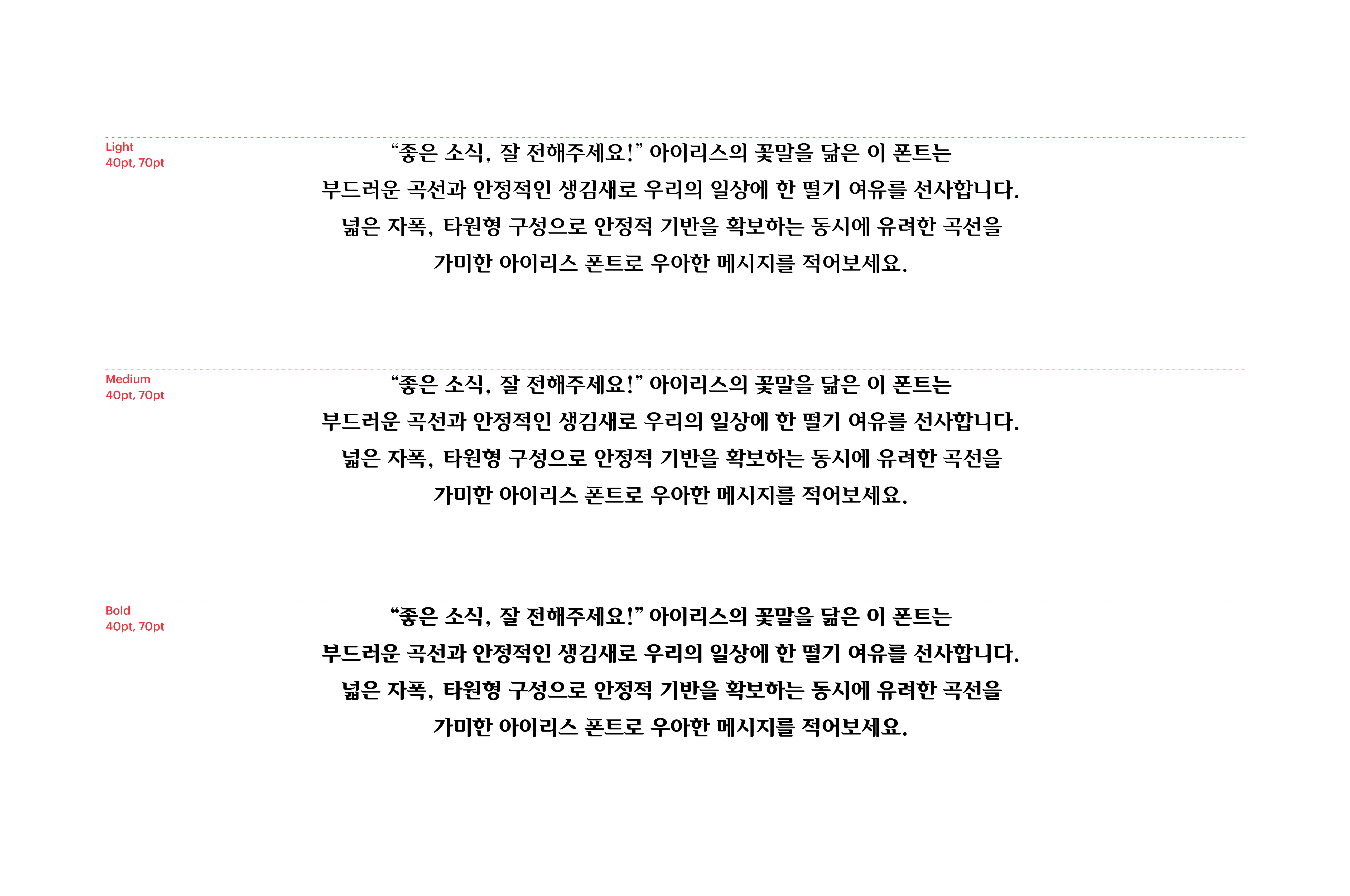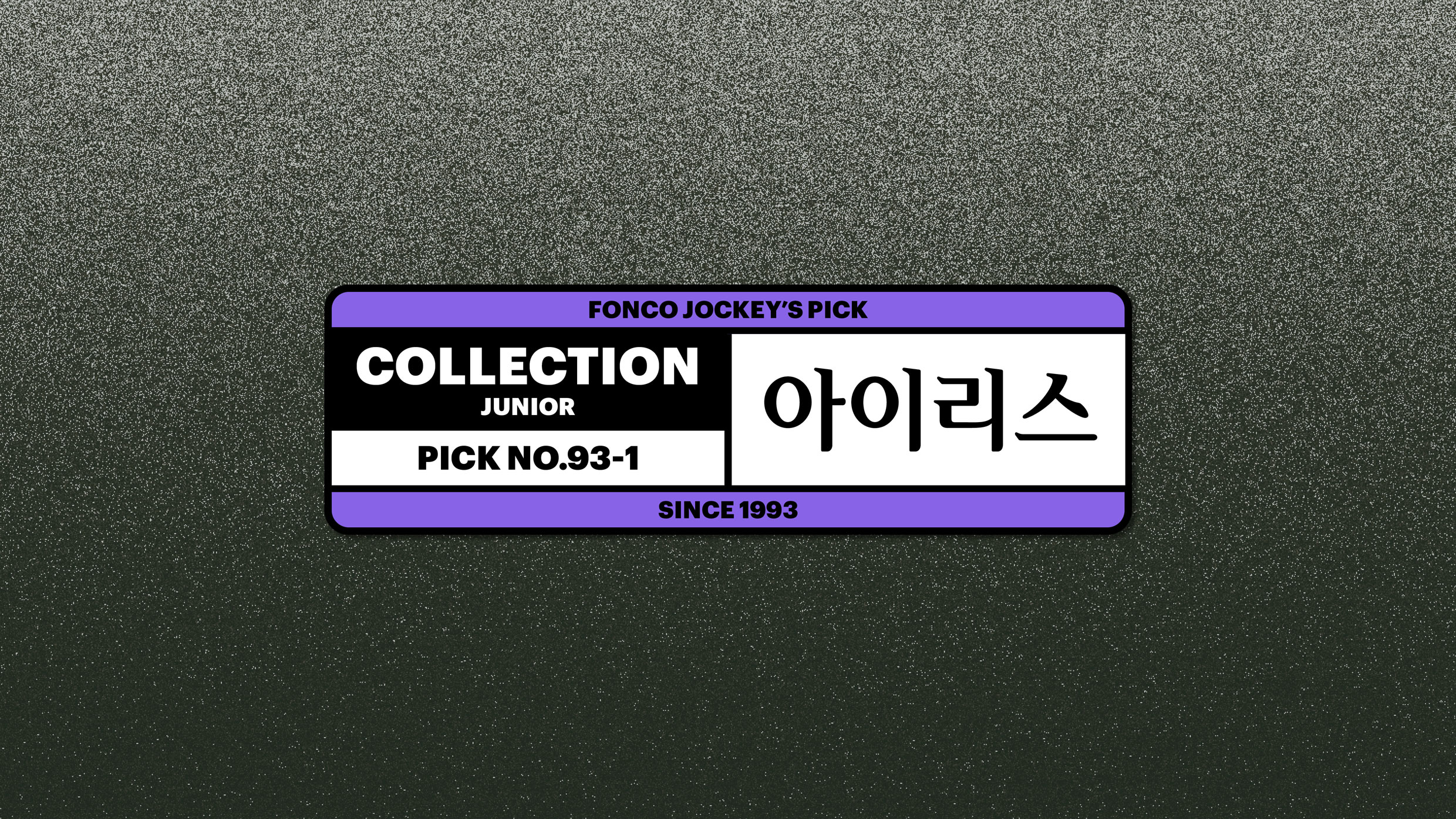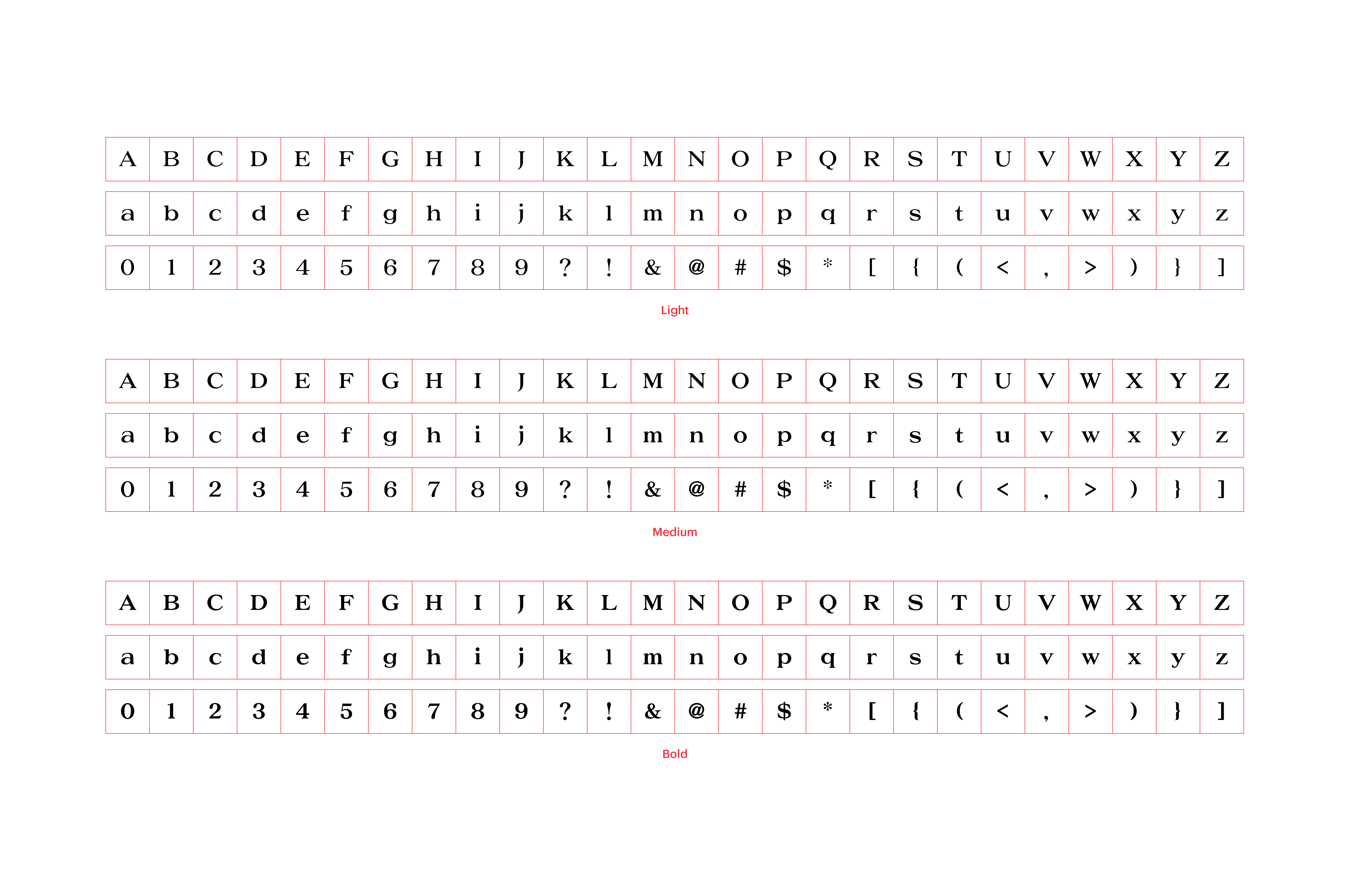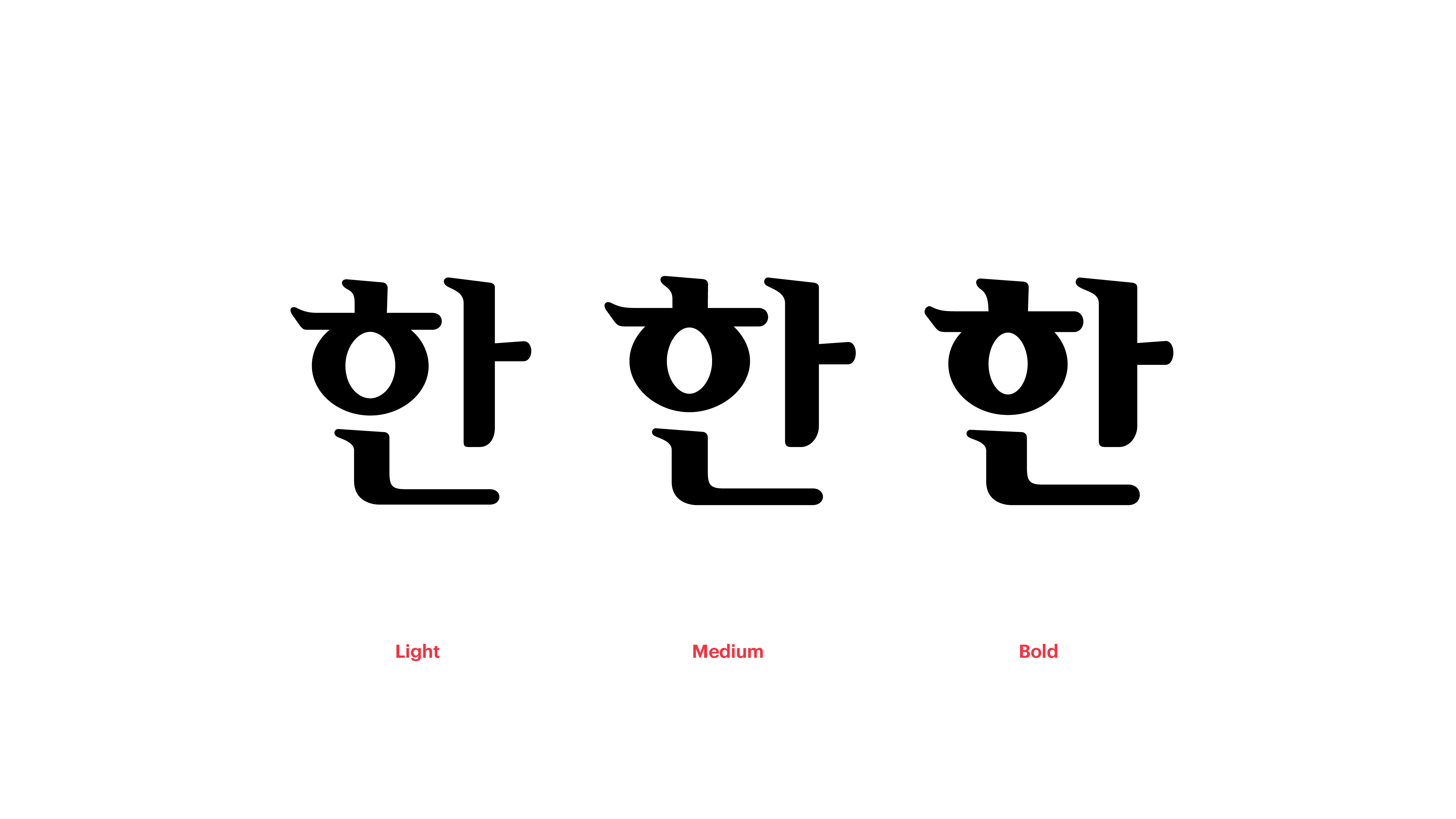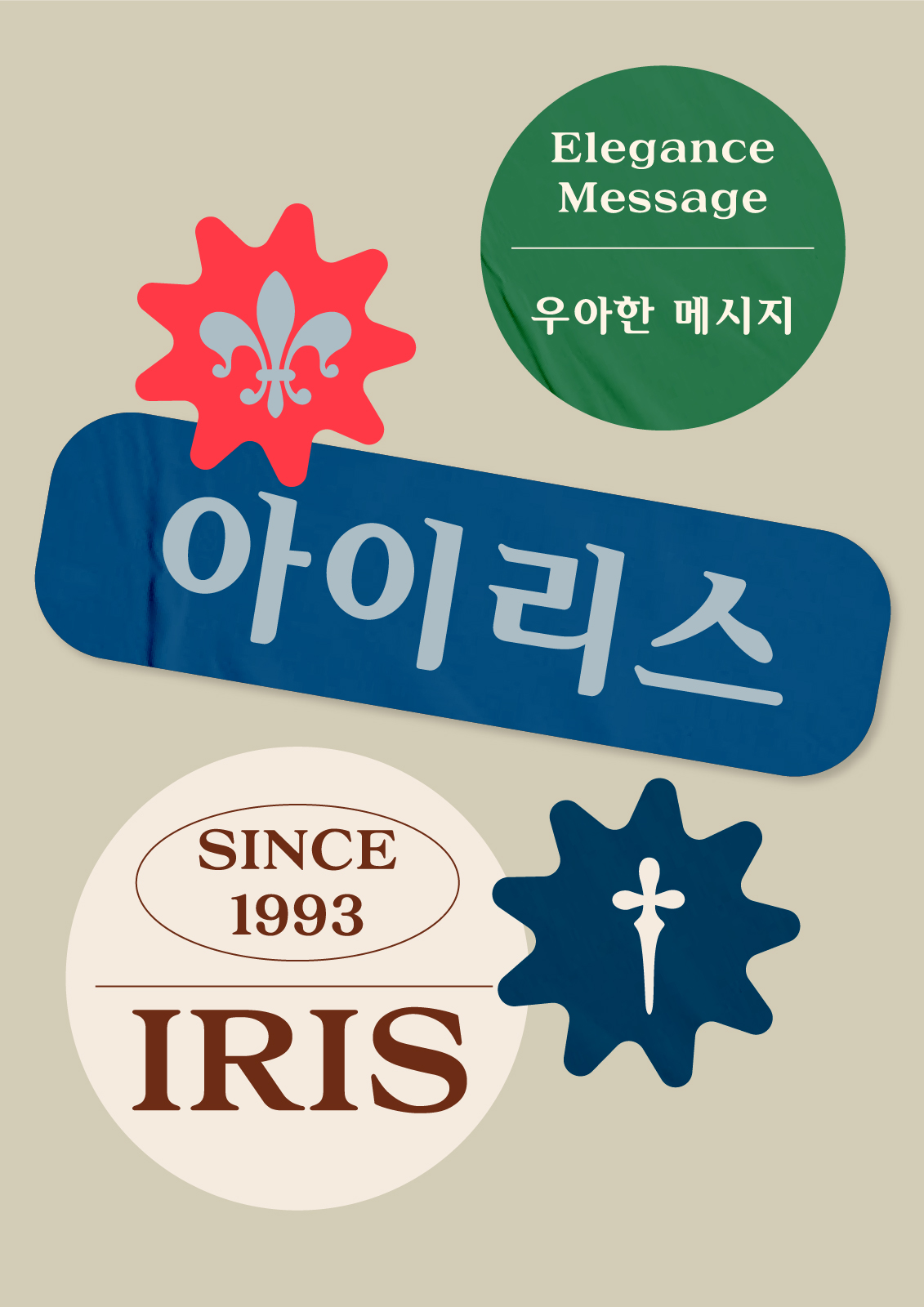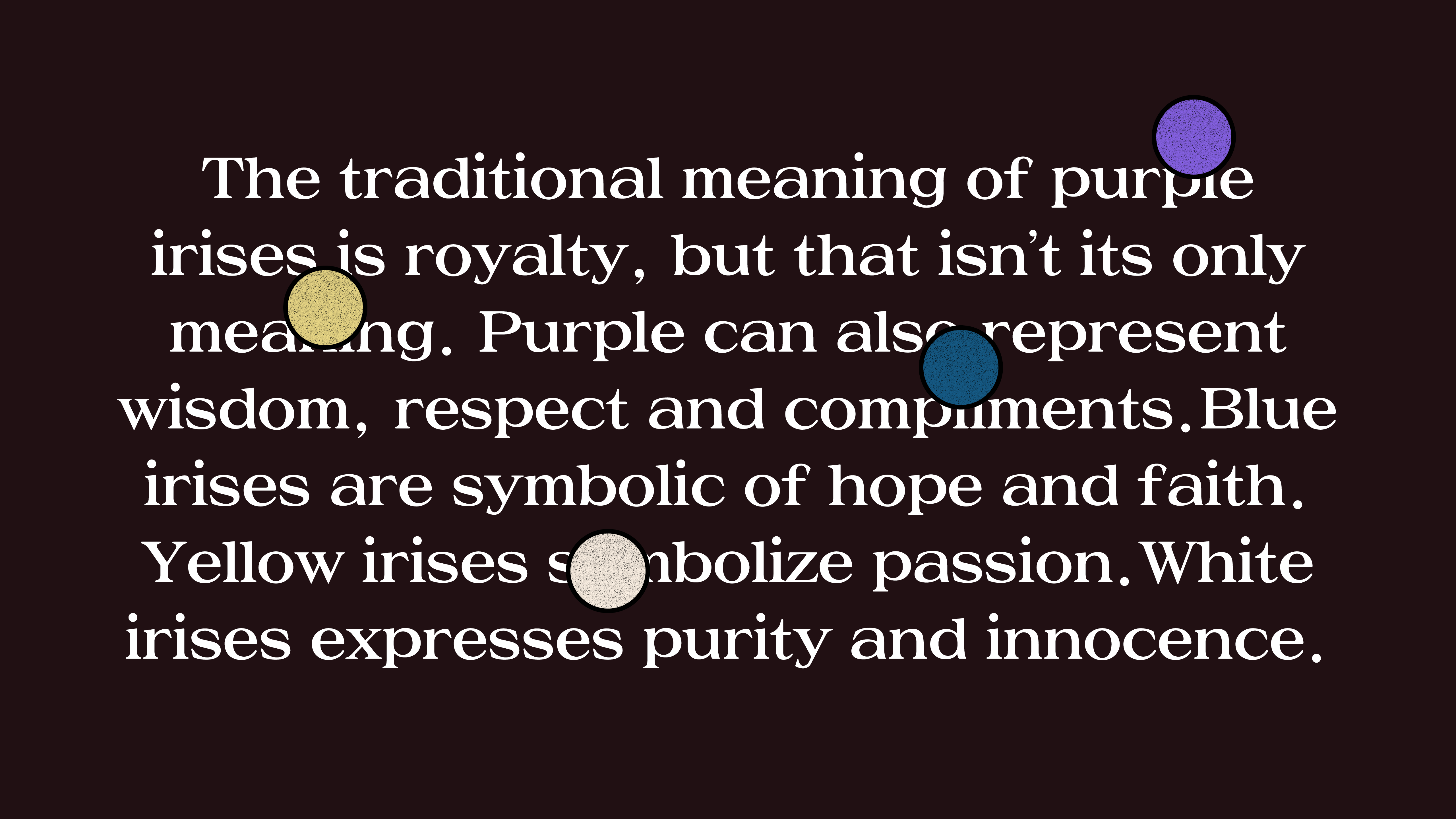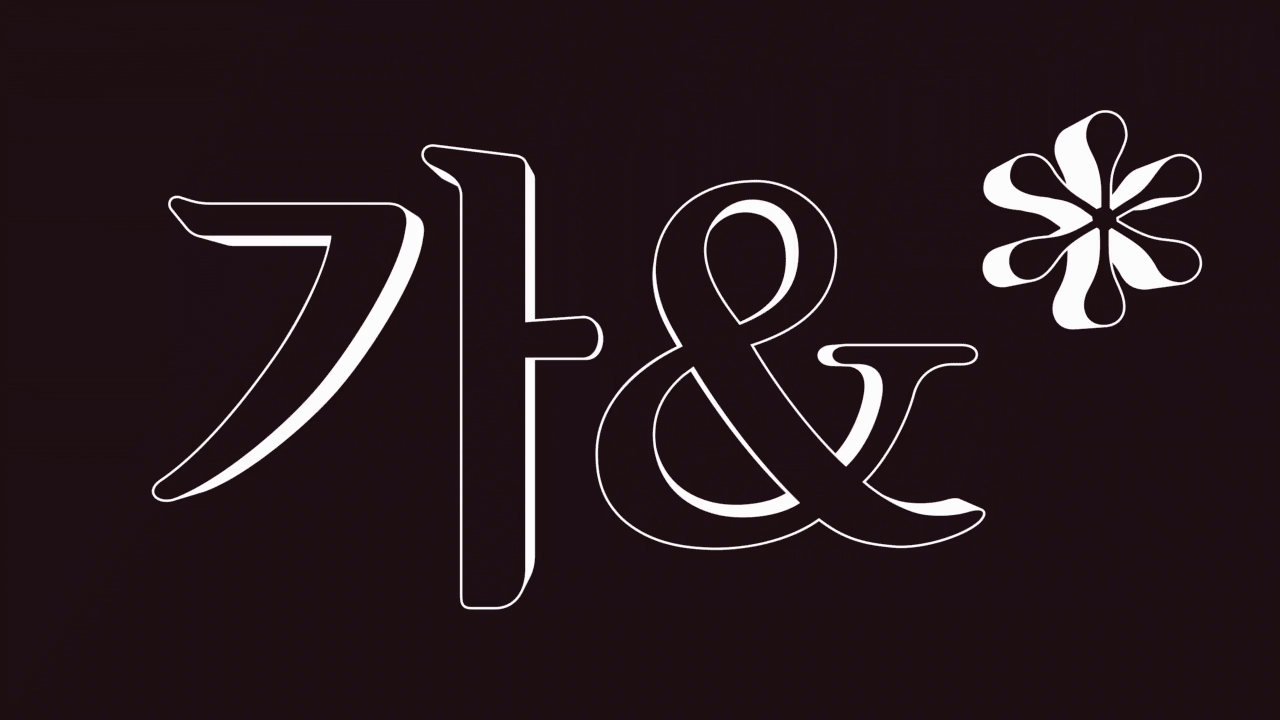
아이리스
1990-1994
Yoon 아이리스
“좋은 소식, 잘 전해 주세요!” 아이리스의 꽃말을 닮은 이 폰트는 부드러운 곡선과 안정적인 생김새로 우리의 일상에 한 떨기 여유를 선사합니다. 넓은 자폭, 타원형 구성으로 안정적 기반을 확보하는 동시에 유려한 곡선을 가미한 아이리스 폰트로 우아한 메시지를 적어보세요.
한글 2,780자 / 라틴 95자 / 라틴 합자 17자 / KS약물 986자